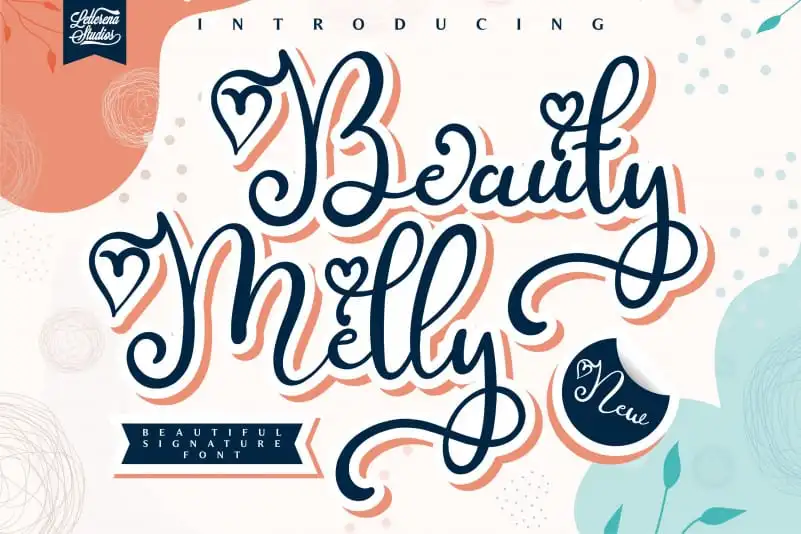
Beauty Melly Calligraphy Font – Download Grátis
A fonte Beauty Melly Calligraphy é uma elegante escolha para qualquer projeto que busque uma mão-dura delicada e romantizadora. Ela se destaca por suas letras bem redondas e distintas, criando um charme único que transformará seus projetos em verdadeiros objetos de desejo. Ideal tanto para o design de cartões de natal quanto para qualquer projeto de craft que precise de um toque romântico, esta fonte script é perfeita. Ela será a escolha certa se você está buscando dar um ar delicado e encantador aos seus trabalhos, criando designs que capturam a essência do amor e da magia do período festivo. Beauty Melly Calligraphy é uma adição ideal para qualquer designer ou amante de design, oferecendo um toque sofisticado e romântico sem sacrificar o encanto natural das letras escritas à mão. Seja você que esteja criando cartões de aniversário poéticos, decorações de casamento personalizadas ou até mesmo impressões no seu blog, esta fonte oferece a combinação perfeita de beleza e delicadeza para suas criações.